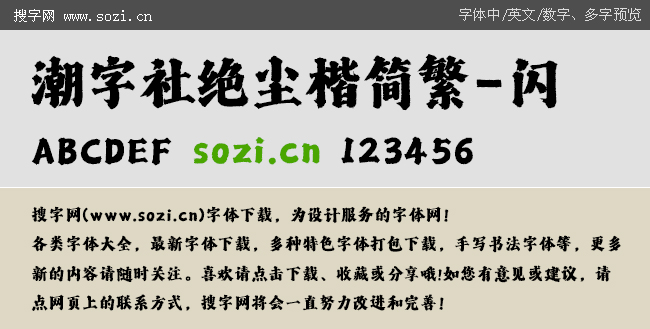
潮字社绝尘楷简繁-闪
搜字网提供一款潮字社绝尘楷简繁-闪中文字体下载,潮字社绝尘楷简繁-闪是一款自然手写楷体,字形古朴稳重大气,起收笔方圆结合,粗细对比强烈,从字形到笔画,无不透露着沉稳与洒脱。适合应用于艺术设计、平面宣传设计、网页设计等领域等应用。(本字体为个人非商用版,商用请联系作者购买授权。官方网址:http://www.reeji.com 联系方式:021-58597892)